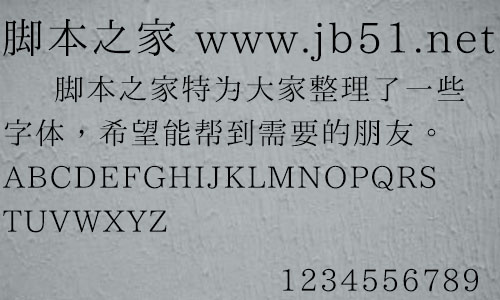
一點(diǎn)明體異體CP是一款不錯(cuò)的可免費(fèi)商用的藝術(shù)字體,字筆觸粗細(xì)適中,書寫端正,具有不錯(cuò)的視覺感,適合應(yīng)用于藝術(shù)設(shè)計(jì)、平面宣傳設(shè)計(jì)、網(wǎng)頁設(shè)計(jì),書法字帖等領(lǐng)域,需要的朋友可以前來本站下載。
「I.明體(I.Ming)」乃系一套依照傳承字形標(biāo)準(zhǔn)化文件《傳承字形部件檢校表》的推薦字形標(biāo)準(zhǔn),并以TrueType格式封裝、依照Unicode編碼的OpenType字型。
我們希望「I.明體」可以作為實(shí)際示范,讓大家明白制作字型時(shí),可以采用依照傳承字形標(biāo)準(zhǔn)化文件推薦字形,同時(shí)仍然依照Unicode編碼、符合OpenType技術(shù),并期待各字型廠商、字型制作者都能仿效,推出更多開源或商業(yè)市場(chǎng)上的傳承字形字型,以收拋磚引玉之效。
「I.明體」這字型名稱里的「I」是羅馬數(shù)字「一」,「I.」念作「一點(diǎn)([粵]Jat1 dim2、[中古]Qjit temx、[客]Jit7 diam3、[北]Yī diǎn、[日]いちてん、[英]One-dot)」,象征筆畫的基本:點(diǎn)與線。